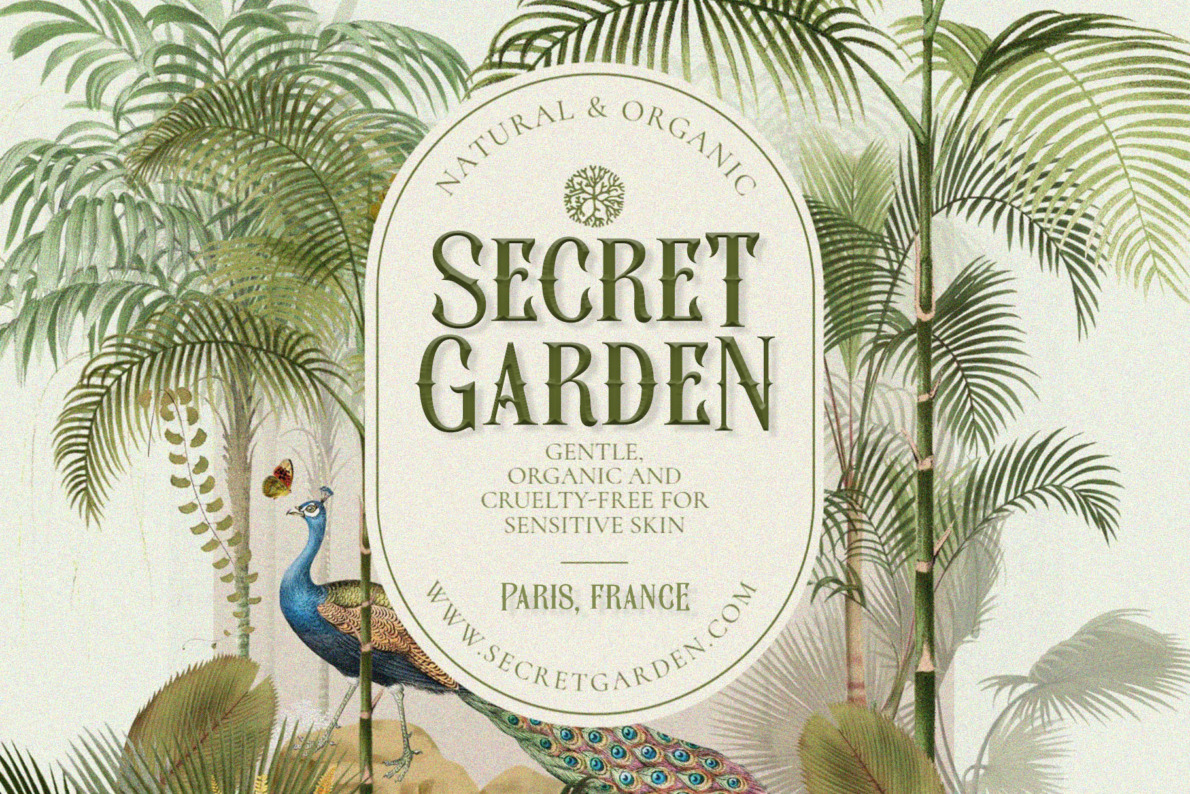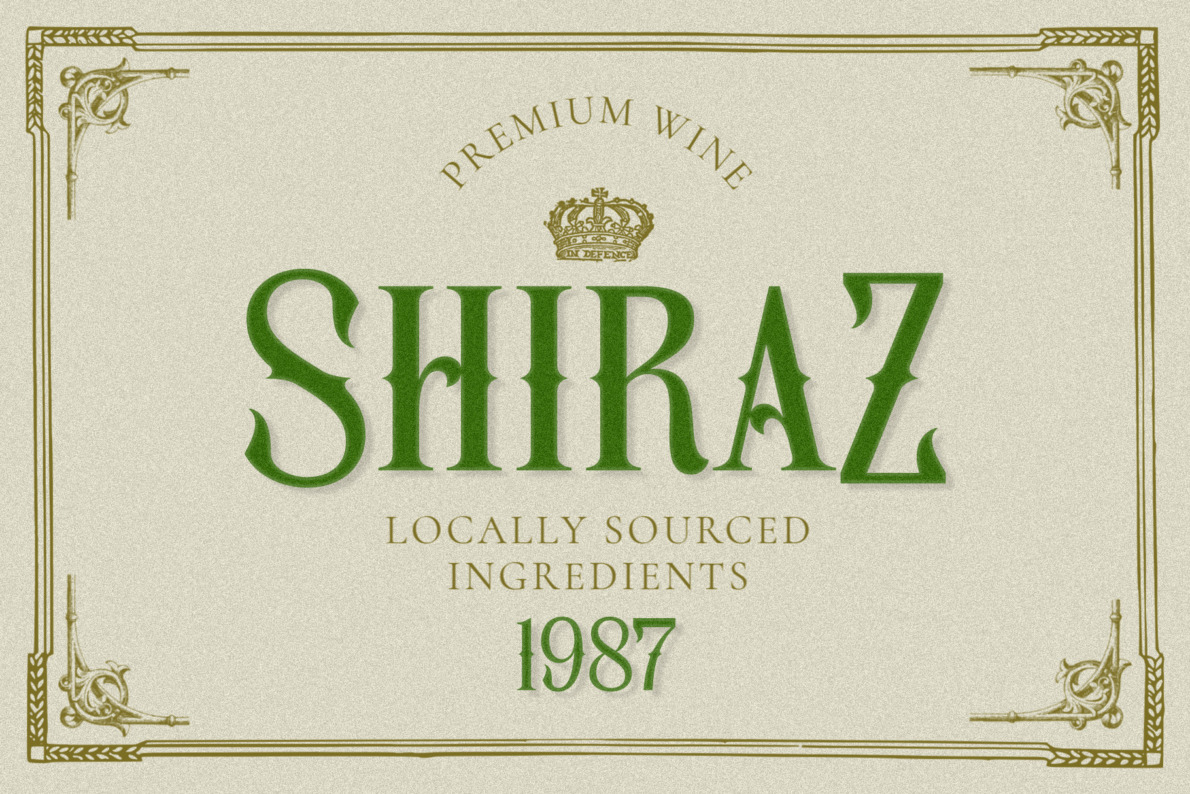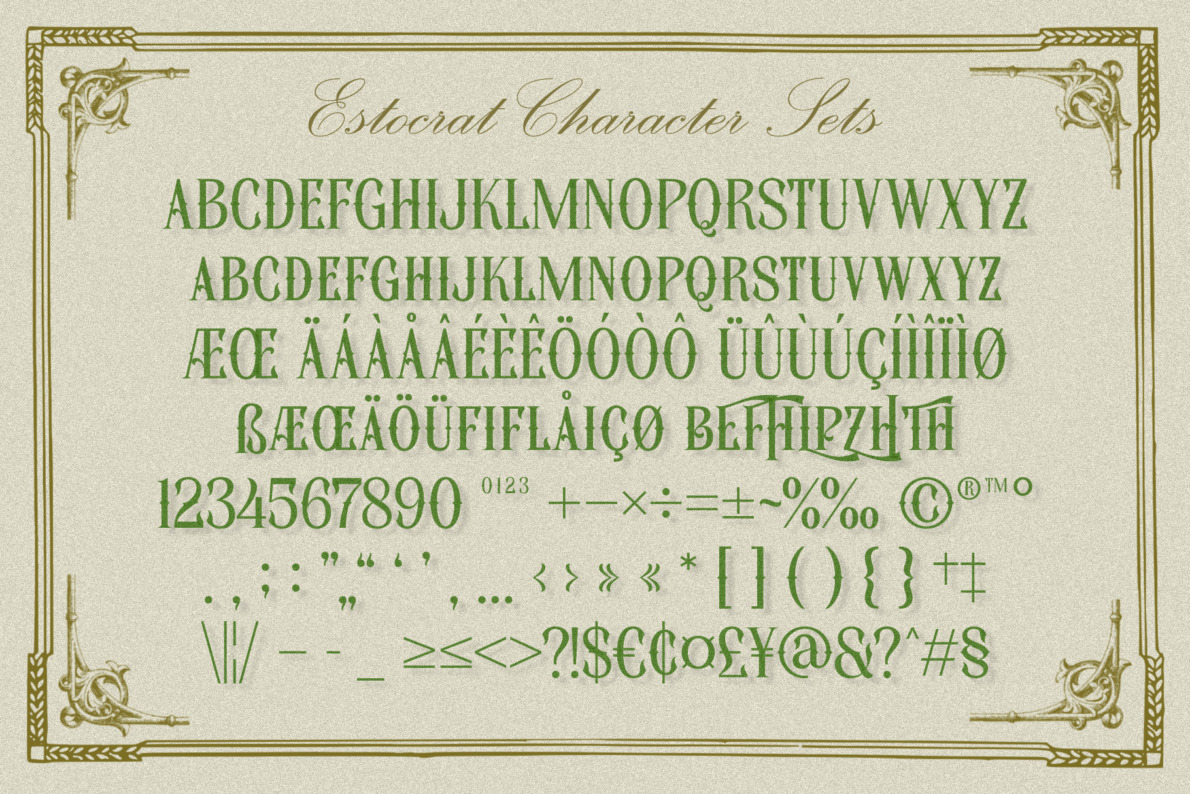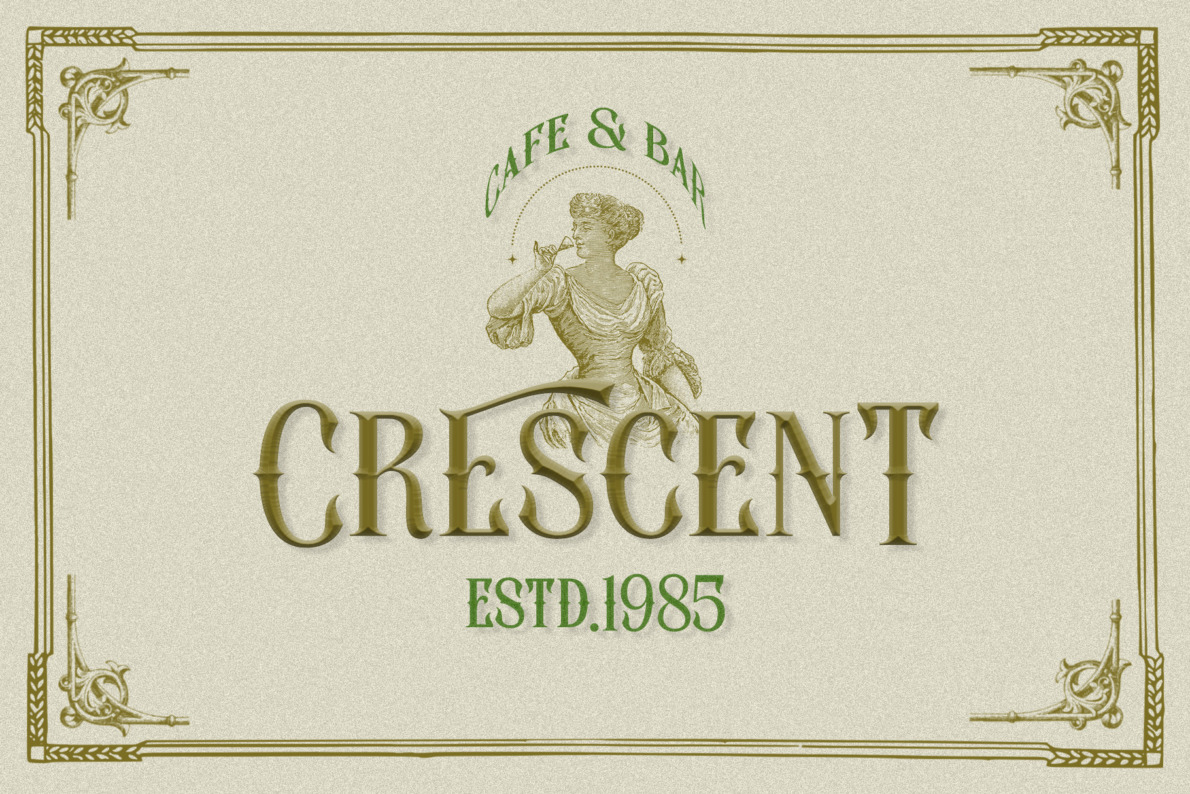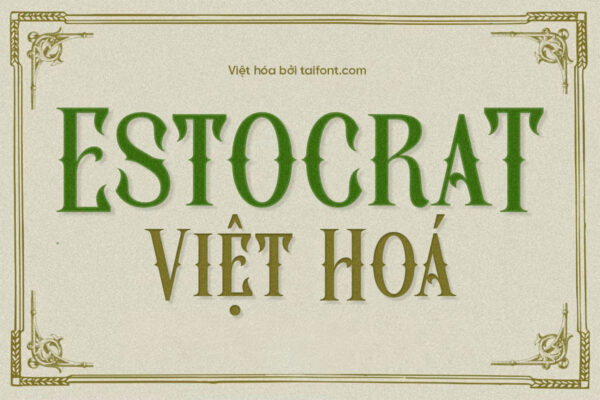
Giới thiệu về Font TF Estocrat Việt hóa
TF Estocrat Việt hóa là một font chữ trang trí nổi bật với thiết kế mang đậm phong cách vintage, cổ điển và đầy quý phái. Font này toát lên vẻ đẹp của sự hoài niệm, tinh tế và một chút uy nghiêm, gợi nhớ về thời kỳ vàng son của nghệ thuật thủ công và in ấn xưa. Những đường nét của Estocrat thường được chăm chút tỉ mỉ, có độ dày vừa phải, mang lại cảm giác vững chãi và đáng tin cậy.
Với đặc điểm là phong thái hoài cổ và khả năng truyền tải sự tinh tế, Estocrat là lựa chọn hoàn hảo cho các thiết kế muốn thể hiện sự đẳng cấp, sự bền vững và một chút lãng mạn của thời gian:
- Thiết kế bảng hiệu cổ điển: Hoàn hảo để sử dụng cho các bảng hiệu của cửa hàng, nhà hàng, quán cà phê, hoặc bất kỳ không gian nào muốn mang phong cách retro, hoài niệm. Font này giúp tạo không khí chân thực, sang trọng và đầy tính nghệ thuật.
- Thiết kế bìa sách: Lý tưởng cho bìa sách văn học cổ điển, lịch sử, hoặc các tác phẩm cần sự trang trọng và chiều sâu. Estocrat sẽ làm cho bìa sách trở nên cuốn hút, gợi cảm giác về một câu chuyện vượt thời gian.
- Thiết kế tem nhãn sản phẩm: Phù hợp cho nhãn hiệu bia, rượu, sản phẩm thủ công mỹ nghệ, hoặc các mặt hàng muốn truyền tải sự độc đáo và chất lượng vượt thời gian.
- Thiết kế nhận diện thương hiệu: Có thể dùng cho logo hoặc bộ nhận diện thương hiệu muốn truyền tải sự vững chãi, uy tín và một chút hoài cổ đầy phong cách.
Với TF Estocrat Việt hóa, bạn có thể dễ dàng thổi hồn vintage, sự sang trọng và vẻ đẹp cổ điển vào các thiết kế, tạo ra những sản phẩm không chỉ đẹp mắt mà còn đầy cảm xúc và chiều sâu.
Font Việt hóa TF Estocrat – Phong chữ vintage cổ điển